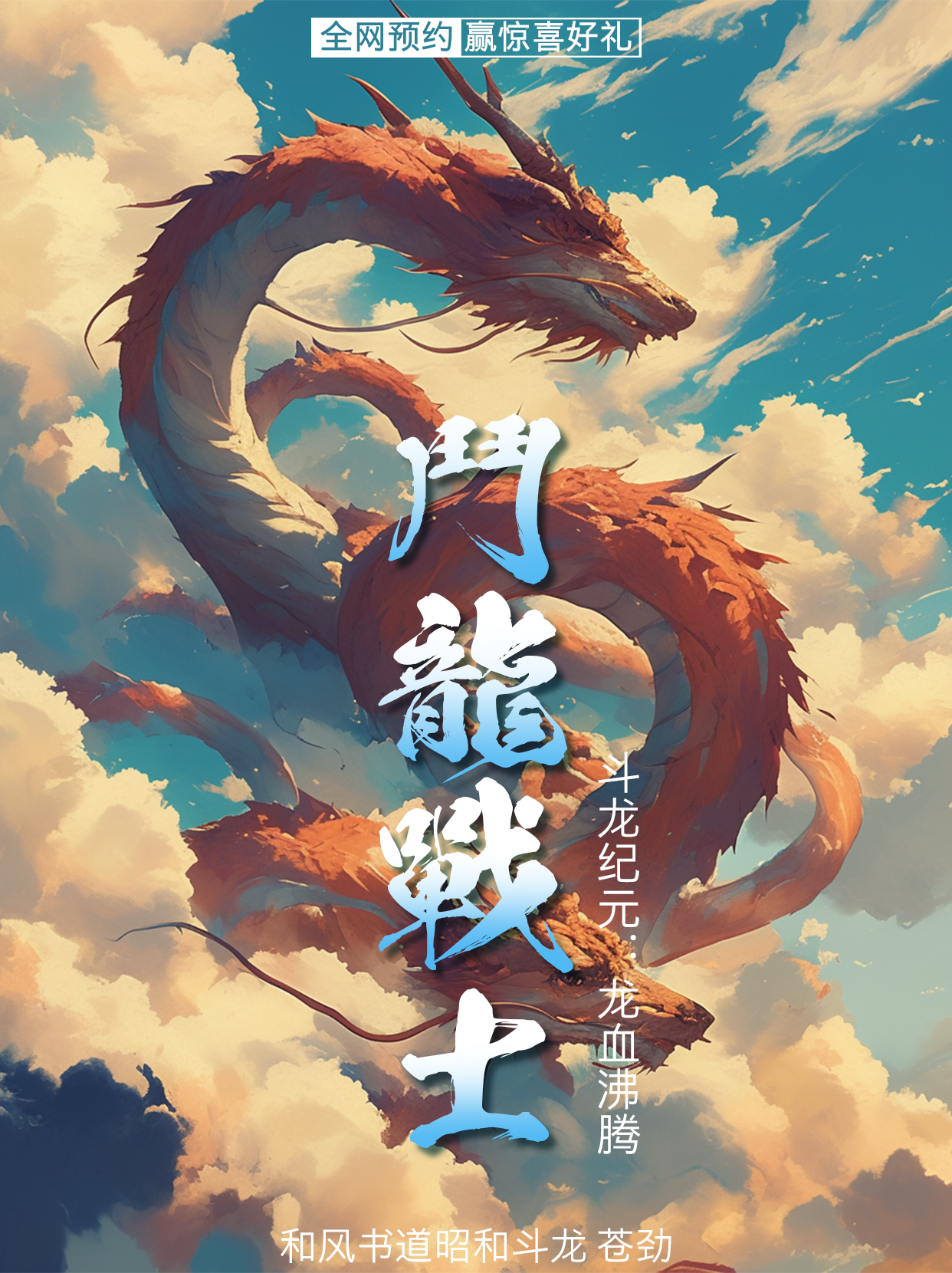
和风书道昭和斗龙 苍劲
GEETYPE-DoulongGBT Black
字体名称:
和风书道昭和斗龙 苍劲
书体类型:
书法字体
字体语言:
简繁
字体类型:
标准
字符集:
GBT
字体字重:
Black(特黑)
整体单字造型十分洒脱,结体松驰有秩,枯笔飞白贯穿其中,进而笔画遒劲有力。用笔灵活洒脱、方劲有力,运用笔画间的牵丝连带丰富字体风格。